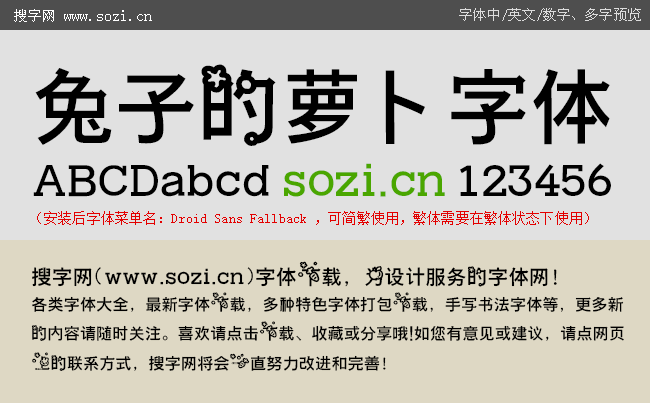
兔子的蘿卜字體
搜字網(wǎng)給大家提供一款兔子的蘿卜字體手機(jī)中文字體下載。這款手機(jī)字體是以黑體字體為原形,字體進(jìn)行了一些簡單變化,筆畫間又嵌入了可愛的卡通圖案。具有黑體端正易認(rèn)的風(fēng)格,卡通味也特別濃,特別適合喜歡手機(jī)字體個性一些的朋友在手機(jī)上安裝使用。